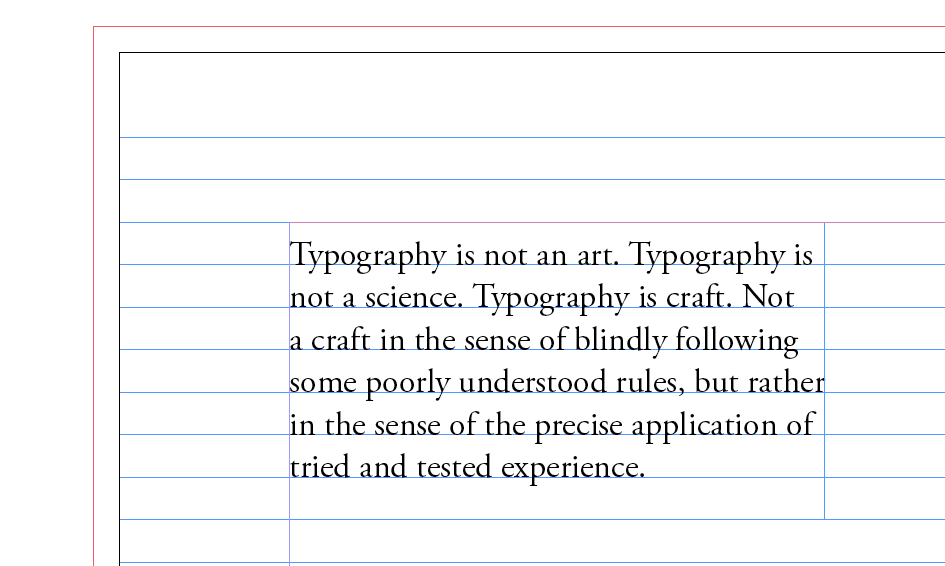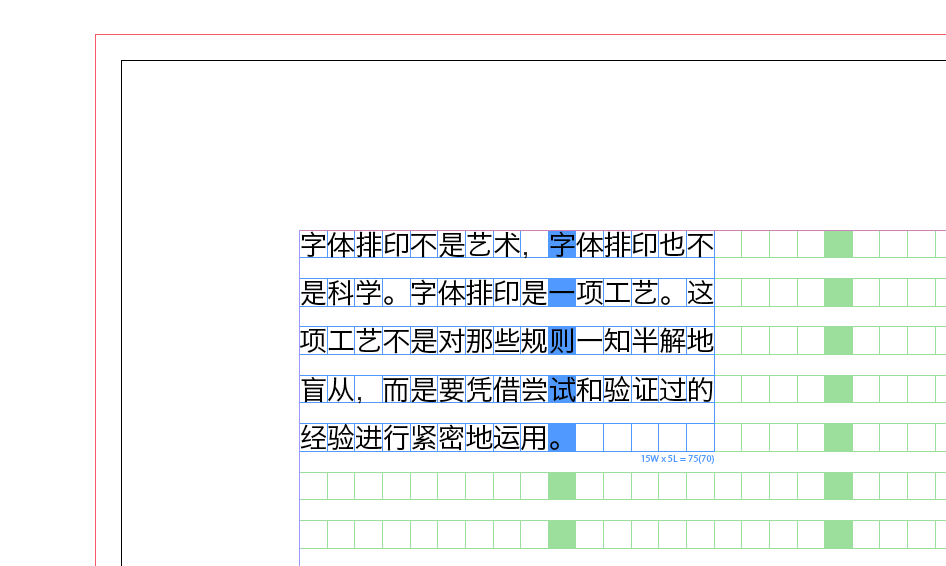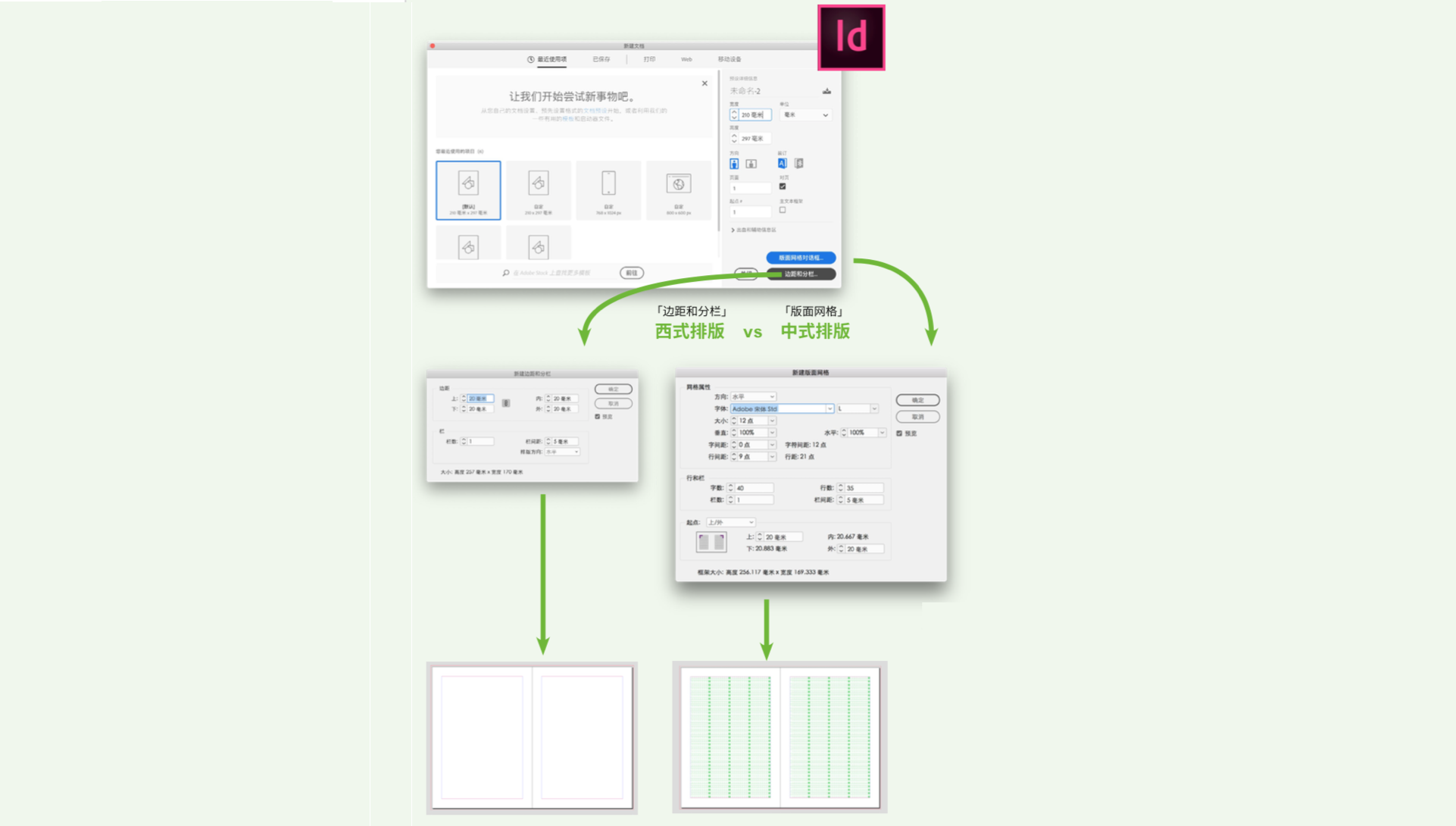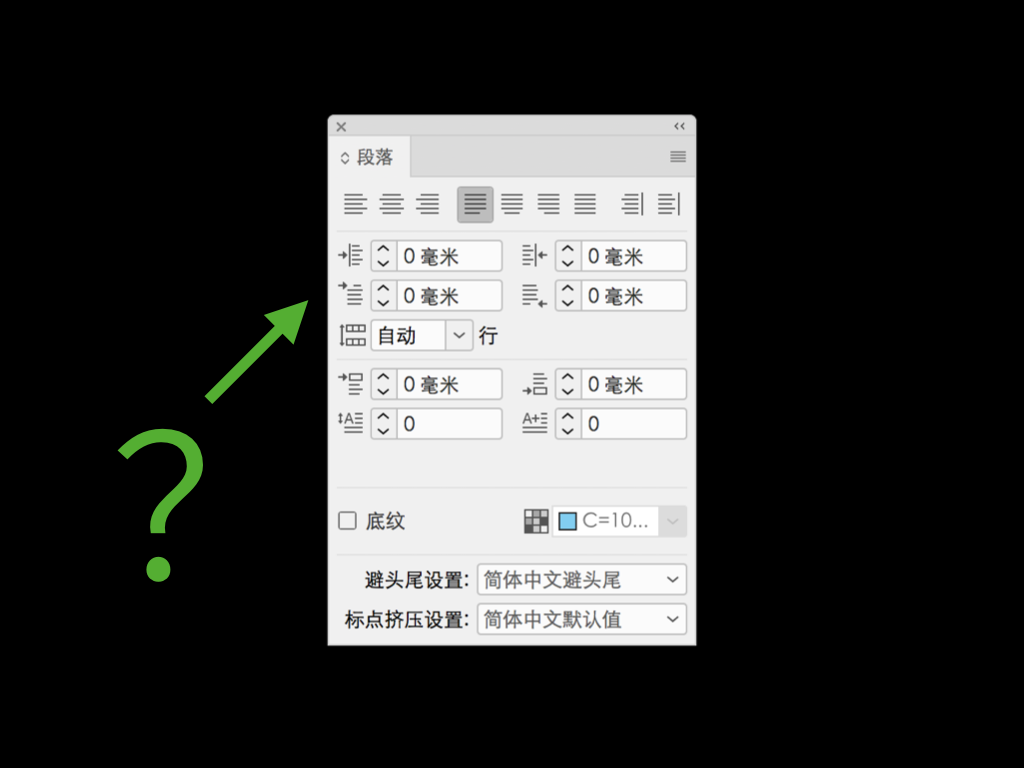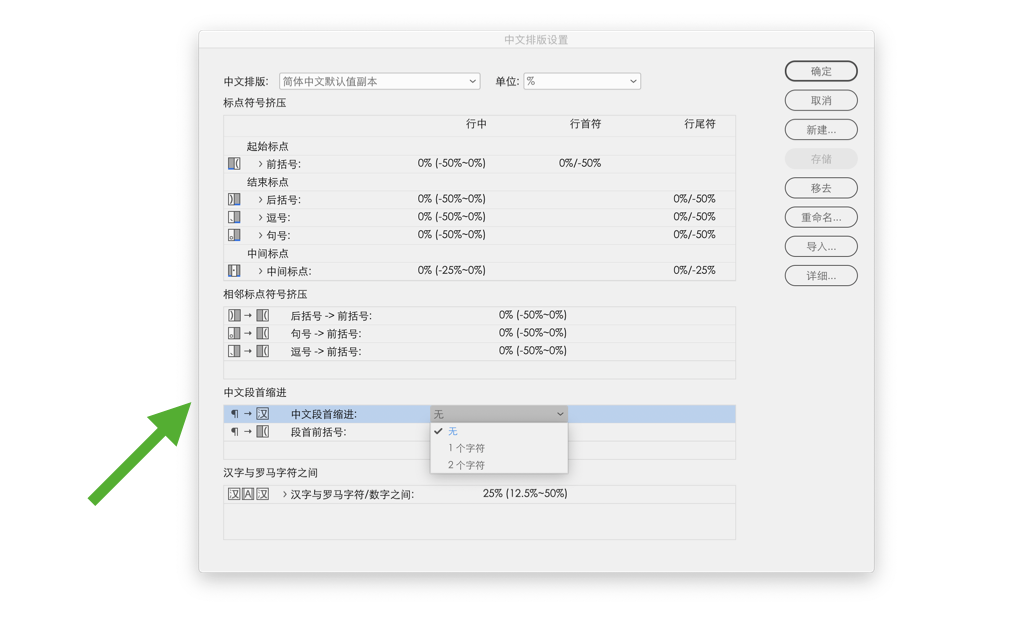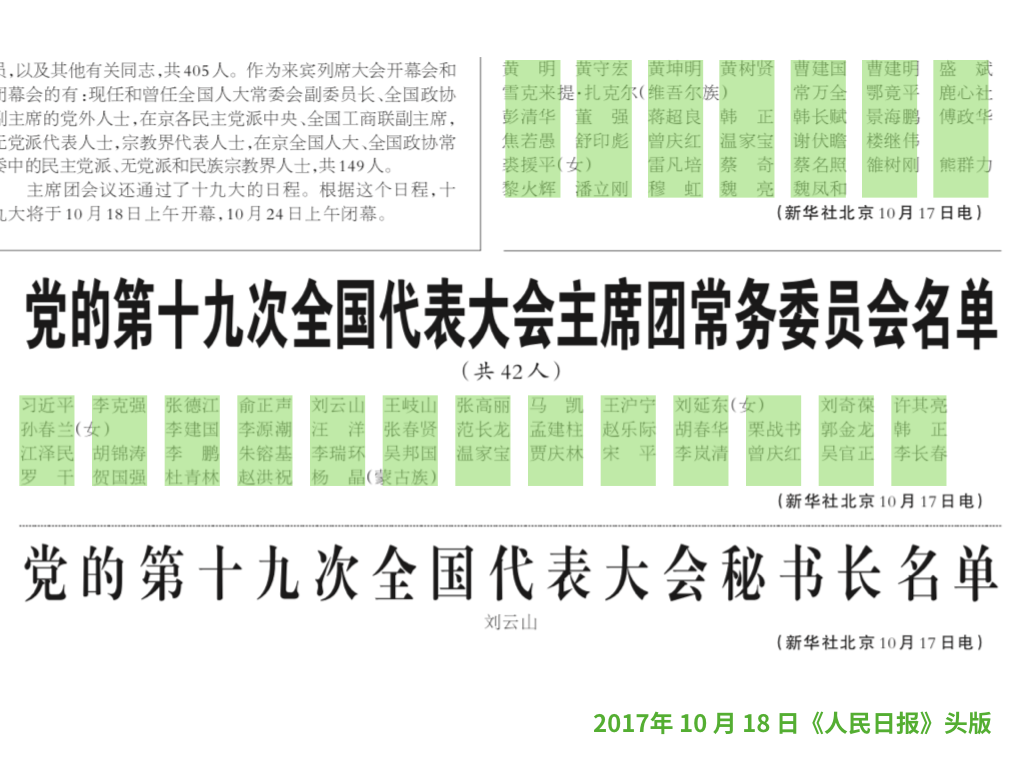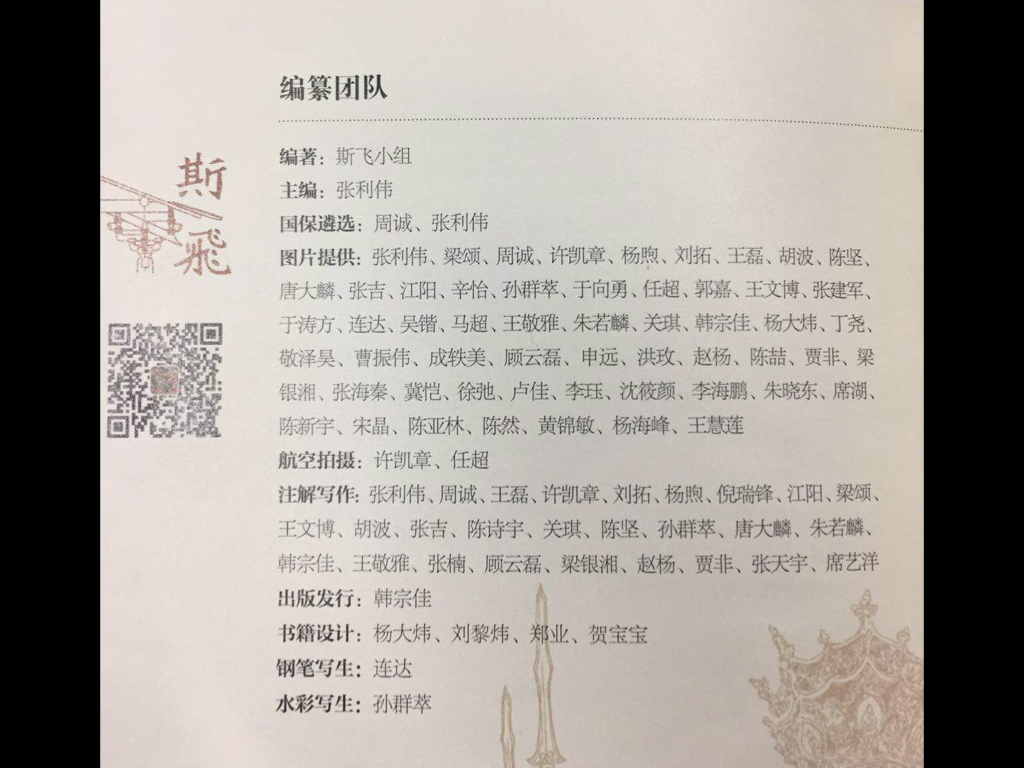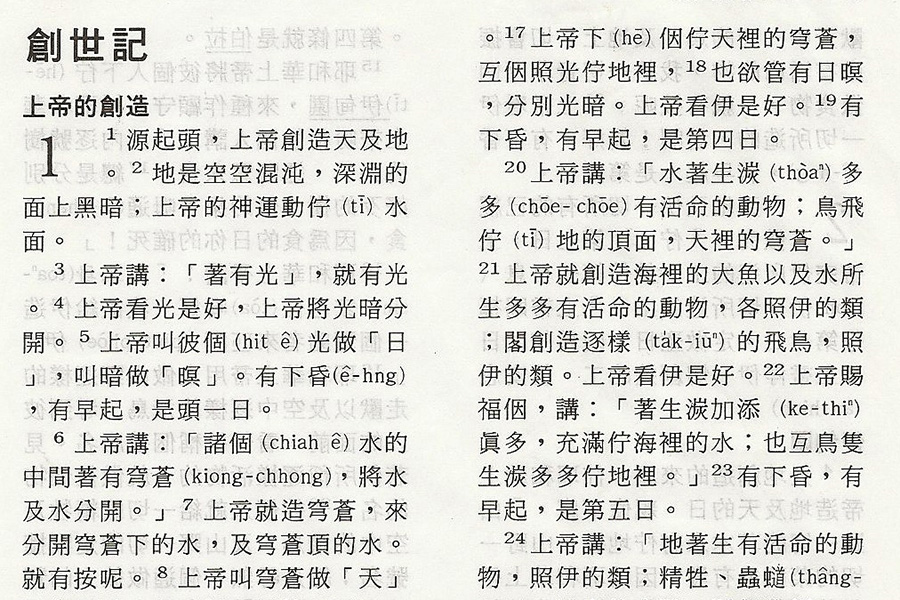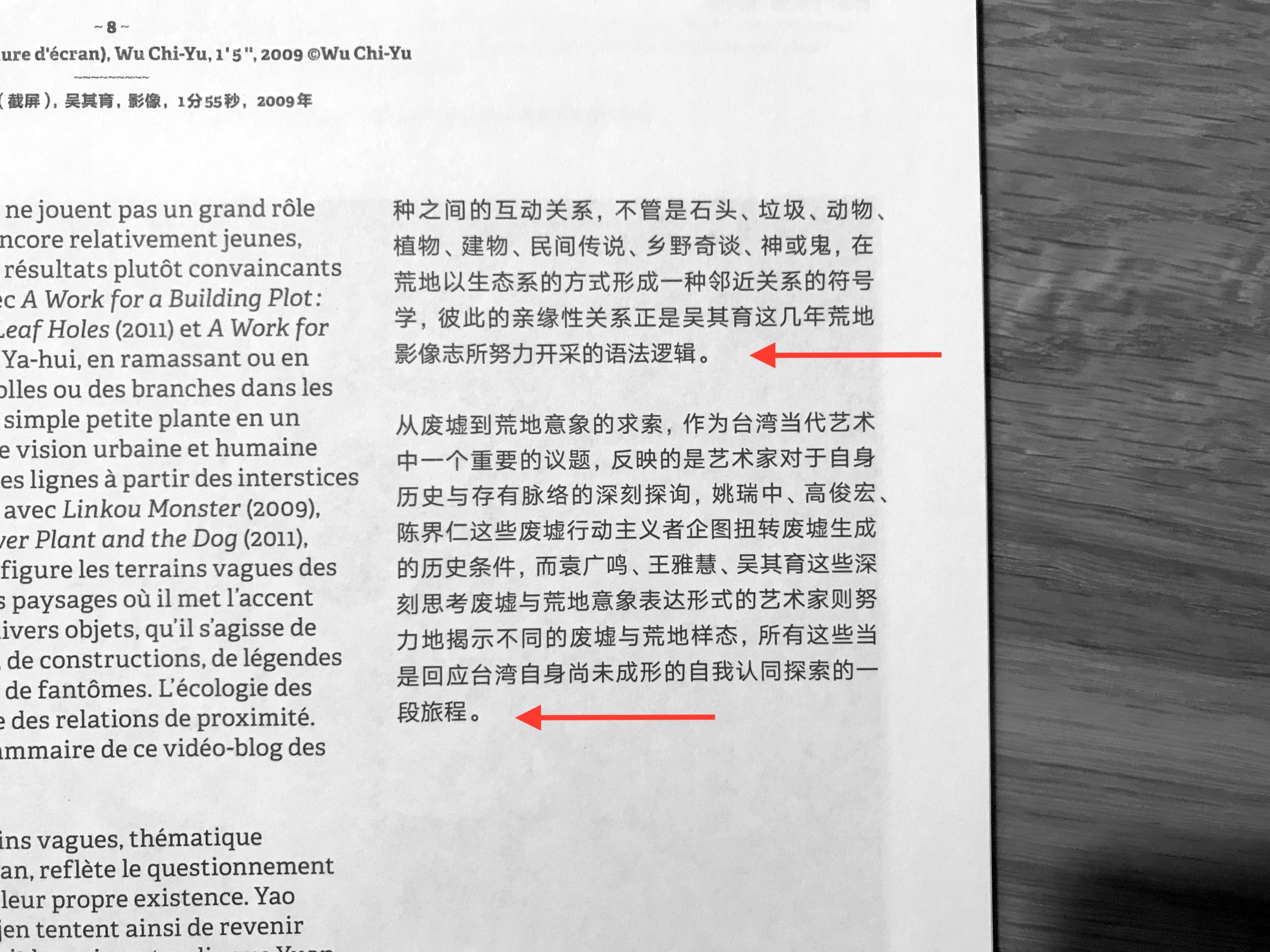
「孔雀计划:中文字体排印的思路」系列倡导从中文出发、以中文的思维方式讨论中文排版。本篇将着眼于宏观字体排印与微观字体排印的关系,从中文排版的底层本质为大家理清对「网格」的各种迷思。
也许对于很多设计师来说,版式设计中最经典的一个工具就是「网格」。瑞士现代设计的代表设计师约瑟夫·米勒–布罗克曼 (Josef Müller-Brockmann) 在半个世纪前整理出了一套西方的网格系统理论,被平面设计师们奉为圭臬,其著作《平面设计中的网格系统》也是设计师必读之书。该书于 2016 年发行简体中文版时,笔者也参与了监修工作。
理论重在实用。近年来,有很多设计师一方面没有吃透西方设计理论中「网格系统」的内容,另一方面又缺乏对中文网格的学习,把西方网格理论生搬硬套到中文排版里,做出了一些看似有网格、实际上却完全不符合中文体例的排版。本文就针对这些现象,对网格系统在中文排版中应用中常见的误区和迷思做一简单的分析。
在讨论开始之前,笔者必须指出本文讨论的重点对象是「编辑设计」中字体排印的情况,即主要针对书刊杂志以及长文阅读的网页的排版。这与整体视觉、海报等平面设计的「版式」的情况应该区别对待,敬请诸位读者留意。
迷思之一:网格是「舶来品」
很多设计师总觉得「网格系统」是诞生于瑞士「国际主义风格」的一个舶来品,现在拿来用都显得很「洋气」。可实际上,仔细阅读布罗克曼的《平面设计中的网格系统》会能发现,作者在书中后半部分「设计案例」中特别提到了东亚的网格系统,并以日文杂志《艺术手帖》的排版为例,明确写道「日文与中文一样,都是建立在正方形的基础上。」
在汉字文化圈,无论是在中国还是日本,传统报刊杂志的「定版设计」都是采用方格稿纸。也就是说,在设计版面时先要定下「基本正文字号」「基本正文行距」绘制出稿纸,即中文的基本网格。之后,在针对所有的标题、分栏等元素,不以毫米、点为单位,而都是以「字」「行」为基本单位进行设计。比如,对每个板块的设定都是按照「宽度占多少字、高度占多少行」的算法,绝对不会出现类似「行长/栏宽为 20.15 个字」这类尴尬的宽度。
以这种「稿纸模式」为基准进行排版计算的思路是真正从汉字方块字出发的、为汉字服务、符合汉字方块特征的方法,从铅字时代开始传统印刷行业就一直遵守这个模式,而这个流程在现代排版软件(如 Adobe InDesign、方正飞腾/飞翔)中同样也可以准确实现。
西文排版中本没有「格」。在西方古登堡式印刷术诞生以来很长一段时间,西文一直只有「分栏」,而直到后来对版面控制的要求逐渐提高,需要更多的参考线才另外定义出网格。与西文不同,「方块汉字」的属性决定了汉字本身就是「一字一格」,因此对于中文来说,网格本身是已蕴含在中文字体排印内部的一个基本元素,可以从一个字格扩展到整个版面网格,这个网格绝对不是舶来品。
在本系列文章的《「中西之别」重考》一文中笔者已指出,中文原生的网格系统就是所谓的「稿纸模式」,这个模式最具有中文特色,最能反映中文的需求,也更能体现和发挥中文排版的特性,而版面中最小网格即正文字号的正方形。这个「字格」是西文所没有的概念——中文可以套用西文橫格稿纸,但是用中文稿纸写西文就非常别扭。
当然,中西网格在本质上并非是水火不容。会熟练使用网格的设计师都有这样的经验,即单位网格画得越小,运用起来就越灵活。而中式网格就可以看成是西式网格系统的一个特例:把单位网格做成一个正文汉字大小,此时中西网格的概念就实现了融合。
迷思之二:做版式先留边距
如前所述,中文排版的基本单位要以「字格」计算,所以文本框的宽度即「一行排多少字」,必须要根据字宽计算。这对于方块汉字来说理所当然,也是必须的。
而西式排版的工作流程则不同。由于西文没有「字格」,因此采用「先算边距,再剩下版心」的做法,将页面剩下中间的部分当做版心填满文字即可。对于很多技法谙熟的字体排印师来说,往往还会套用各种版心样式,甚至会利用数学计算,采用「黄金分割」这类无理数(无限不循环小数)的比例数值来设置版心、栏宽。另一方面,西文字母本身就是比例宽度(所谓的「不等宽」),长文排版也多用左对齐而不用两端对齐,而且即使在两端对齐时也能灵活调整,较好地填满版心,因此对于文本框宽度没有严格要求。
然而,中文里的方块汉字决定了中文不具有西文的灵活度。事实上,传统中文出版界的做法与西文正好相反,是「先算版心,再余白」:
当版面确定后,设计者的任务就是确定版心的尺寸,以及版心在版面上的占位。以文字为主的出版物,在确定版心的尺寸时,是以排版正文字号的字数来确定行长(即版心宽度),再以行数和行间空距之和为版心长度。——《实用出版与印刷工作手册》(第二版),1998年,印刷工业出版社。
由于方块汉字本身一字一格,因此中式排版必须先计算栏宽(比如每行 25 个字)定下版心之后,再把版心摆放到页面上。至于页边距里的天头、地脚、切口、订口这些「余白」的数值,是页面减去版心之后计算出来的,也就是说,并非事先「定」出来、而是之后「余」出来的。如果像西文那样先定边距,再去套汉字,这样的版心套上汉字就很容易出现不足一个汉字宽的零碎值。如果以这样非整字数倍的版心宽度/行长设置里再进行「两端对齐」,字距肯定不可控。
在中国传统的印刷术里,无论是雕版时代还是活字时代,一直都是先在书框里「套格」再进行「摆书」的。中西文种的差异是版式设计里工作流程差异的根本原因。这是传统做法,也是中文网格的起源,只要汉字是方块字,「字格」总是存在的。
迷思之三:不知中文排版的「占字」「占行」为何物
接上节所述,中文排版有了稿纸模式的基础网格之后,所有元素都是通过「占格」「占行」的描述来进行定位。这样的表述其实司空见惯,却往往很难按照西文方式(包括以西文思路开发的排版软件)的方式实现,比如
- 中文段首缩进要「空两格」——西文的缩进多用点、毫米等绝对单位设定
- 中文花名册里的人名列表宽度以「占三格」为栏宽——西文多用大网格通过 tab 对齐
- 中文小标题的高度「占三行位置」——西文多通过段落间距进行控制
- 中文栏间距为「占两个字」宽度——西文多依照网格用点、毫米等绝对单位设定
占字处理
由于汉字是中文网格的最小单位,所以在处理中文排版的时候,各元素都统一采用「占几个字」来描述。甚至连行内的标点符号也如此,比如在中国国标 GB/T 15834—2011《标点符号用法》中采用的用法都是「句号占一个字位置」云云。
而小学语文课上老师要求的「段首空两格」这样简单、基础的要求,居然很少能正确地在现代排版中被复现。很多设计师在使用 Adobe Illustrator 及 InDesign 等专业排版工具时,费力地去用「段落」面板里原本为西文排版流程设置的功能、别扭地用毫米去定义段首缩进,却不知道软件本身实际上已经配备了更为方面的、为中文排版而特别设置的功能如何使用。
「花名册」也是一个富有中文特色的排版方式。中文的花名册即「人名列表」在正统的排版里往往需要按照「占三格位置」的占字法进行排版,比如下图中报纸所采用的方法。由于基础网格是「占三格」,因此,如果姓名过短,比如仅有两个汉字,则需要在姓名之间加一个字宽的空,以便与三个汉字的姓名对齐;反之,如果姓名过长或者加带其他信息,则其后的姓名不是固定空一格起排,而是必须依照「占三字」形成的网格,从下一个网格开始的地方开始排,以实现对齐。
非常遗憾的是,现在有很多平面设计师都不知道这种传统排版的占字排版格式,对人名列表的处理也是当做普通文本复制粘贴了之。原本可以用网格排得整整齐齐的版面,却被搞得乱七八糟。
另一方面,从电子书和网页排版方面来看,CSS「盒子模型」的本质从某种意义上说与中文网格非常类似。而 CSS 中的 em 单位即来自印刷排版的所谓「全角」,作为一个相对单位,其实际数值等于字号,使用这个单位就可以直接按「字格」进行定义了。大多数前端工程师也知道,在网页和电子书中实现「空两格」应该将值定义成 2em 而不是直接用 pt 或者 px 等绝对单位。
另外,CSS 中字号 font-size 还有一个看似奇怪的 rem单位,这个单位其实正是依照字格原则而导入的。rem 即 root em、即相对于 root 要素指定的単位,定义的是根元素(root element)的字号。使用这个单位的实际效果即相当于,用正文字号定义出了一个基本网格,也就是「字格」,然后所有其他元素都按照这个网格的倍数进行定位,即「占几个字」。前述普通的 em 是相对于父元素的倍数,会「继承」「遗传」,所以在许多层嵌套后 em 中就很容易迷失,从而带来无法预知的错误风险;而 rem 则直指根元素 ,只需要在根元素确定一个固定值,之后就可以随时拿来调用,清晰明了。这样,网页页面设计思路就能传统印刷页面工作流程的「定版设计」接轨,这也是当时熟悉东亚排版的专家们为何要极力导入 rem 单位的原因。
占行处理
如果以目前常见的横排考虑,「占字」是对横向度量的定义,那么「占行」就是纵向度量的定义。传统中文排版中,页面中非正文元素(比如标题、插图)应该如何摆放,应该通过「占几行」来描述。从思维方式来说,尽管这些非正文元素会临时打破基础字格,但由于是通过占行描述,因此能让其很好的服帖于基础字格,让它们「万变不离其宗」。
在排版中,所有标题都必须是正文行的倍数。——《当代排版技术概论》第二版,1994 年,印刷工业出版社。
所谓标题的占行,是指在标题排版中,它所占的版面位置应是正文行的倍数。所谓对行,就是在一个版面上和一本书中,所有对应的正文字行都处于一个水平位置上。当所有的标题都是按正文行的倍数排版占位时,自然就能帮助正文对行的要求。 ——《实用出版与印刷工作手册》第二版,1998年,印刷工业出版社
很明显,采用「占行」的计算方式可以保证通栏「对行」,版面会更整齐美观,也能提高文章的易读性。
在传统的金属活字排版习惯中,「接排的一级标题约占四五行;二级标题约占二三行;三级标题约占一二行」等等都是常见做法。而且,标题本身也可能不只一行,因此会有「双行题目占三行」这样的操作。这里「占行」当然都是以正文字号为依据说明所占地位,清晰易懂。
然而,由于当代大多数的排版工具都采用的是西文的行距计算法则,对于插入段落间的小标题,多采用「段落间距」的方式进行控制。这样做「对行」并不是不能做,而是相当繁琐,尤其是当时小标题的字号与正文不同时,需要认真计算才能保证网格对齐。
而数码时代的电子排版又如何占行呢?用 CSS 实现「纵向韵律」(Vertical Rhythm) 一直是中西文共通的难题。W3C 曾发布过CSS Rhythmic Sizing 的文档,已经很长时间没有更新,而从「占行」的角度来说,最为接近的属性可能应该是 line-grid,但目前由于专家们针对既有网页如何兼容等问题还有很大争议,这份草案还在激烈讨论中,前景非常不明朗。
当然,网页的纵向韵律控制在具体实践中遇到各种难度,与行高的计算有关。行高问题之所以复杂,是因为前端在进行「CSS 排版」时,实际上并无法预知会在什么平台、通过什么浏览器读取到哪个字体的什么度量信息进行计算,因此交给排版引擎实际渲染时,这其中的每个步骤都有太多变数。因此对于前端工程师来说,在写 CSS 时需要依照最终实现效果而进行妥协决策。这在本篇里不便展开,有兴趣的读者可以参考我们的播客「字谈字畅」第 103 期节目「行高行距行行行」。
迷思之四:过犹不及地认为「齐就是好」
正如前述,采用字格的中式网格进行排版时,只要控制好那些「非全宽元素」,就能很好地进行中文网格的「纵横对齐」。显然,这些「非全宽元素」包括调整宽度的标点符号、比例宽度的阿拉伯数字和混排在行内的西文字母。所以,如果要执行「网格绝对优先」原则,就可以采用简单粗暴的逻辑,把所有标点用全宽,不调整也不执行避头尾,所有数字和西文都采用全角,那么排出来的自然是「纵横对齐」。
但问题是,这样排出来的效果在造型上是整齐了,但是真的容易读吗?
走路是为了达到目的地,路虽然要平坦,不能坑坑洼洼,但是也不能像大雪原的冰面一样过于平滑,不仅容易跌跤,而且没有树木等参照物反而容易失去方向。同样,阅读是为了获取内容,人眼在扫描文字列的时候自然要顺畅、不能凹凸不平,但也不能过于平整,不仅容易跳行,还容易导致困乏。任何事情都不能矫枉过正,在做排版的时候千万不能单纯为了形式而牺牲内容。
本站编辑钱争予早在 2013 年就曾撰文《纵横对齐不是现代方法》。作为现代汉语的表记形式,既然现代中文已经不能没有标点符号,那么现代中文排版必须对其进行认真细致地调整,根据易读性进行细致的标点宽度调整、避头尾处理及换行位置处理,以优先保证易读性。对于混排的阿拉伯数字和西文,也要在现行编辑层面的正字法检查的基础之上(比如权衡使用阿拉伯数字和汉字数字,比如夹杂的西文改用中文词汇等),再进行形式的选择(比如在竖排时合理地采用所谓「全角字符」)。不应该一味让内容妥协于形式,单纯表现形式美的「纵横对齐」,这样的效果这也绝对不是合理使用网格系统的必然结果。
迷思之五:一蹴而就地认为「网格只用来定文本框」
作为《平面设计中的网格系统》日文版监修,日本设计师白井敬尚先生曾说过:「网格系统并不是一种单纯地对页面进行分割手法,而是要在理解字号、行距这些排版基本构造的基础之上才能成立。」因此在中文排版中使用网格系统,就必须要从中文的字号、行距的基本特性开始考虑,才能从本质上活用网格系统。
纵观市面上的中文印刷品,虽然有很多中国设计师说在使用网格,而实际上只是拿西式网格概念硬套在中文上,定出文本框之后就根本不去管文本框内字格问题,拉出的文本框里行长不是字号的整数倍,各行字距不等,根本谈不上去细究行内字格内部的细节。
如前所述,由于汉字本身一字一格,中式网格可以具体到行内。这也是为什么 Adobe InDesign 东亚版需要另外增设「水平网格工具」「垂直网格工具」让用户去设置文本框,而不是像西文那样只是一个简单的框框。而且,在使用中式网格进行微观字体排印时,总是要权衡「优先网格对齐」「打破网格制约」的利弊,进行版面调整。否则,网格形如虚设,段落排出来很容易变得稀疏不匀。
那么,什么是中文排版「具体到字格」的中式网格思维方式呢?在此可以举一个简单例子。在使用所谓「半角式」以及「开明式」排版时,经常会使用「对开」(或者称为「半宽」「二分」)宽度的标点符号。当一行字有偶数个对开标点时,最终行长依旧是整数倍。如下图第三行,其中两个逗号都采用半宽,这两个半宽加起来刚好是一个全宽,这一行依旧是整的。此时,虽然第一个逗号后面的几个字偏移了半格(图中淡绿色部分),但每格依旧字距均匀,并且能在第二个逗号之后又重新向网格对齐。
但是,如果像图中第二行那样,只有奇数个标点时,多余的半个字宽应该如何调整呢?
在活字排版时代多为手工操作,因此会采用工序尽量少、最有效的方式。因此如左图,由于第二行行内有且仅有一个逗号,因此把多余的半个字宽加在逗号后面,实际效果等于将半宽逗号改为全宽。虽然全宽逗号的空略为显眼,但这样既通过清晰显示行内最大的停顿处保证了文章易读性,又让调整范围限于标点而不用去挪动其他字符的字距,还让这一行字保持了网格对齐。
而在后来的照排时代,更多地会对第二行进行两端对齐处理,也就是将多余的半个字宽均摊到每一个字距中,效果如图右。这是活字时代绝对不可能采取的方法,一来活字时代找不到恰好合适厚度的铅空,二来这要求排版工要在每个字后面都手动添加铅空,操作极其繁琐。这样的「均摊」操作,优点是添加的空隙不如左图明显(而且行越长、字数越多越不明显);缺点是这一行的字距被拉大,与上下行都不一样(行越短、字数越少越明显),破坏了「密排」原则。从网格的角度来看,这个操作让第二行的所有字都偏移了网格,而且偏移量与第三行不同,实际上导致了三行字都具有不同的阅读节奏。
这其实只是排版中非常简单且常见的调整实例,这两种方法没有对错之分,只是风格之别。从网格的角度来看,由于需要调整,完全的纵横对齐既然已经不可能达到,那么就只能「尽量」保持部分对齐。如果「优先网格对齐」,可能左图好一些;如果对字距要求不那么细致,采用右图的方式,就必须「打破网格制约」。排版总是需要妥协,关键是在于妥协是否合理,是否与设计逻辑对应。这些才是在微观字体排印中,为了保证读者流畅的阅读体验而需要关注的地方。
小结:是参考线,还是金科玉律?
网格是一个便利的工具,其本质与方块汉字「字格」的特性一致,直接扎根于中文排版的基础之中。以网格为工具进行定版设计,灵活进行占字、占行,能非常高效地,在保证易读性的基础上实现多样化的中文版式。但另一方面,网格终究只是一个工具,需要「活用」而不能「死用」。我们既不能上纲上线地强制所有字符「纵横对齐」,也不能像噎废食地用西式网格随便拉文本框之后就放任不管。实现阅读流畅、版面精致的中文排版,需要以网格为依据,以中文易读性为指标进行具体定夺。哪些是基本原则需要遵守网格,哪些需要活用去打破网格,这既是网格工具的活用精髓,也是用网格排版的乐趣所在。